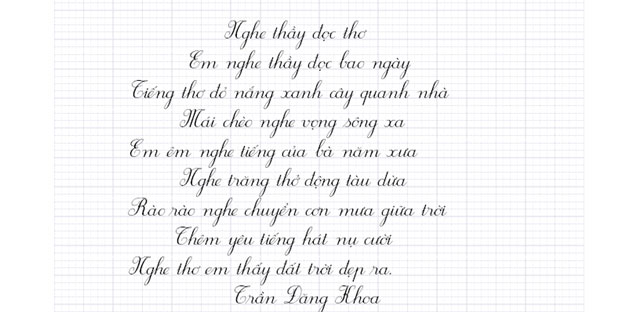
Nhiều giáo viên và phụ huynh khi tải font chữ tiểu học thường gặp tình trạng font cài được nhưng hiển thị sai ô ly, lệch dòng hoặc thiếu dấu tiếng Việt. Điều này làm tài liệu luyện viết mất chuẩn, học sinh khó quan sát và giáo viên cũng tốn thêm thời gian chỉnh sửa. Trong bài viết này, Xưởng In Viva tổng hợp các bộ font chữ tiểu học dễ dùng, hiển thị rõ và phù hợp cho cả soạn giáo án lẫn in tài liệu học tập.
Tổng hợp 04 bộ font chữ tiểu học được sử dụng phổ biến
Hiện nay có khá nhiều bộ font mô phỏng nét chữ tập viết dành cho học sinh tiểu học. Tuy nhiên, không phải font nào cũng phù hợp với tài liệu dạy học thực tế. Một số font chỉ đẹp về hình thức nhưng lại không khớp với dòng kẻ ô ly hoặc thiếu ký tự tiếng Việt, khiến quá trình soạn bài và in ấn gặp nhiều bất tiện.
Vì vậy, trước khi tải font chữ tiểu học, bạn nên tham khảo trước các bộ font đang được sử dụng phổ biến trong giáo án, phiếu bài tập và tài liệu luyện viết. Dưới đây là một số font thường gặp:
| Font | Loại ô ly | Ứng dụng | Phần mềm sử dụng |
|---|---|---|---|
| HP001 | 4 ô ly | Luyện viết | Word |
| HP002 | 5 ô ly | Bài tập tập viết | Word |
| Font tập viết | 4 ô ly | Giáo án | PowerPoint |
| Font tiểu học chuẩn | 5 ô ly | Tài liệu học tập | Word |
Khi tải font chữ viết tay tiểu học, bạn nên kiểm tra kỹ loại ô ly, bảng mã và khả năng hiển thị tiếng Việt. Đây là ba yếu tố ảnh hưởng trực tiếp đến chất lượng tài liệu sau khi in ra cho học sinh sử dụng.
Font chữ tiểu học là gì?
Font chữ tiểu học là nhóm font được thiết kế dựa trên mẫu chữ viết trong chương trình tiểu học. Điểm khác biệt lớn của loại font này so với font văn bản thông thường nằm ở tỷ lệ chữ, độ cao thấp của nét, khoảng cách dòng và khả năng hiển thị theo vở ô ly.
Khi download font chữ tiểu học, người dùng thường mong muốn tái hiện đúng mẫu chữ để học sinh dễ quan sát, tập tô và luyện viết. Vì vậy, loại font này không chỉ cần đẹp mà còn phải chính xác về cấu trúc chữ cái, vị trí dấu thanh và độ cân đối giữa các nét.
Nhờ đặc điểm đó, tải font chữ tập viết tiểu học được sử dụng rất nhiều trong giáo dục, đặc biệt là ở bậc mầm non chuyển tiếp lên lớp 1 và khối tiểu học những năm đầu cấp.
05 lợi ích khi sử dụng tải font chữ tiểu học chuẩn
Việc sử dụng đúng font chữ tiểu học không chỉ giúp tài liệu nhìn đẹp hơn mà còn hỗ trợ trực tiếp cho quá trình giảng dạy và luyện viết. Đây là lý do nhiều giáo viên luôn ưu tiên chọn đúng bộ font thay vì dùng các font viết tay thông thường.
Dưới đây là những lợi ích rõ ràng khi tải font chữ tiểu học chuẩn và sử dụng đúng cách:
- Giúp học sinh luyện chữ đúng mẫu: font mô phỏng gần sát nét chữ tập viết nên học sinh dễ quan sát và làm theo.
- Dễ tạo tài liệu học tập: giáo viên có thể nhanh chóng soạn phiếu bài tập, bài luyện viết hoặc bảng chữ mẫu.
- Phù hợp với vở ô ly: chữ hiển thị theo dòng kẻ chuẩn, hạn chế tình trạng lệch hàng hoặc sai tỷ lệ.
- Tăng tính trực quan: tài liệu rõ ràng, học sinh dễ nhận biết nét thanh, nét đậm và vị trí dấu tiếng Việt.
- Tiết kiệm thời gian soạn giáo án: không cần chỉnh thủ công từng dòng chữ như khi dùng font thông thường.
Nhờ những lợi ích này, nhu cầu tải font tiểu học ngày càng phổ biến trong giáo viên, trung tâm dạy thêm và cả phụ huynh tự làm tài liệu luyện viết tại nhà.
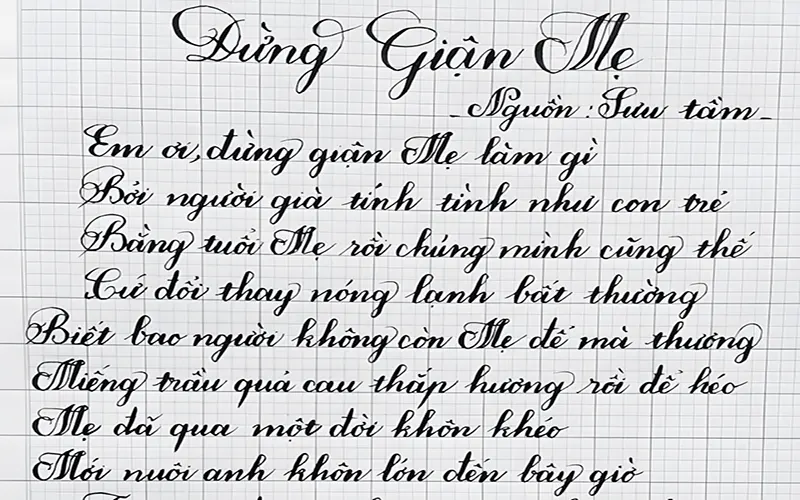
Ứng dụng khi download font chữ tiểu học trong tài liệu học tập
Font chữ tiểu học có phạm vi ứng dụng rộng hơn nhiều người nghĩ. Không chỉ dùng để tạo bài tập tập viết, font này còn hỗ trợ rất tốt trong việc xây dựng các tài liệu trực quan giúp học sinh làm quen với mặt chữ và cách trình bày bài học.
Khi tải font chữ tiểu học chuẩn, bạn có thể sử dụng trong nhiều loại tài liệu khác nhau như:
- Thiết kế bài tập luyện viết.
- Tạo phiếu bài tập về nhà.
- Soạn giáo án tiểu học.
- Thiết kế bảng chữ cái luyện viết.
- Làm sổ tay hoặc tài liệu ôn tập cho học sinh.
- In mẫu chữ để học sinh tô theo.
Nếu chọn đúng bộ font, tài liệu học tập sẽ đồng đều hơn về hình thức và dễ sử dụng hơn trong thực tế giảng dạy. Đây cũng là lý do nhiều người tìm download font chữ tiểu học thay vì dùng font viết tay thông thường.
04 lỗi thường gặp khi tải font chữ tiểu học
Mặc dù việc cài font khá đơn giản, nhưng trong thực tế nhiều người vẫn gặp lỗi khiến tài liệu hiển thị sai hoặc mất chuẩn khi in ra giấy. Những lỗi này thường xuất phát từ việc chọn sai font, sai định dạng hoặc sử dụng nguồn tải không ổn định.
Dưới đây là một số lỗi phổ biến khi download font chữ tiểu học:
- Font không hiển thị trong Word: do cài đặt chưa đúng hoặc font bị lỗi file.
- Chữ lệch dòng kẻ: thường xảy ra khi chọn sai loại ô ly hoặc dùng font không đúng chuẩn tiểu học.
- Font thiếu ký tự: không hỗ trợ đầy đủ tiếng Việt nên dấu bị sai hoặc mất chữ.
- Font không tương thích phần mềm: một số font hiển thị lỗi trong PowerPoint hoặc phần mềm thiết kế khác.
Để tránh những lỗi này, bạn nên kiểm tra kỹ nguồn tải, thử trước trong Word và xem lại khả năng hiển thị khi in ra giấy trước khi sử dụng chính thức.
Hoàn toàn có thể. Nếu chọn đúng font chuẩn và kiểm tra trước khi in, tài liệu sẽ rõ ràng và phù hợp cho học sinh luyện viết.
Tải font chữ tiểu học là giải pháp hữu ích giúp giáo viên và phụ huynh tạo ra tài liệu luyện viết đúng chuẩn cho học sinh. Khi sử dụng đúng bộ download font chữ tiểu học, chữ sẽ hiển thị rõ, đúng dòng kẻ và hỗ trợ đầy đủ tiếng Việt để việc dạy học thuận tiện hơn.